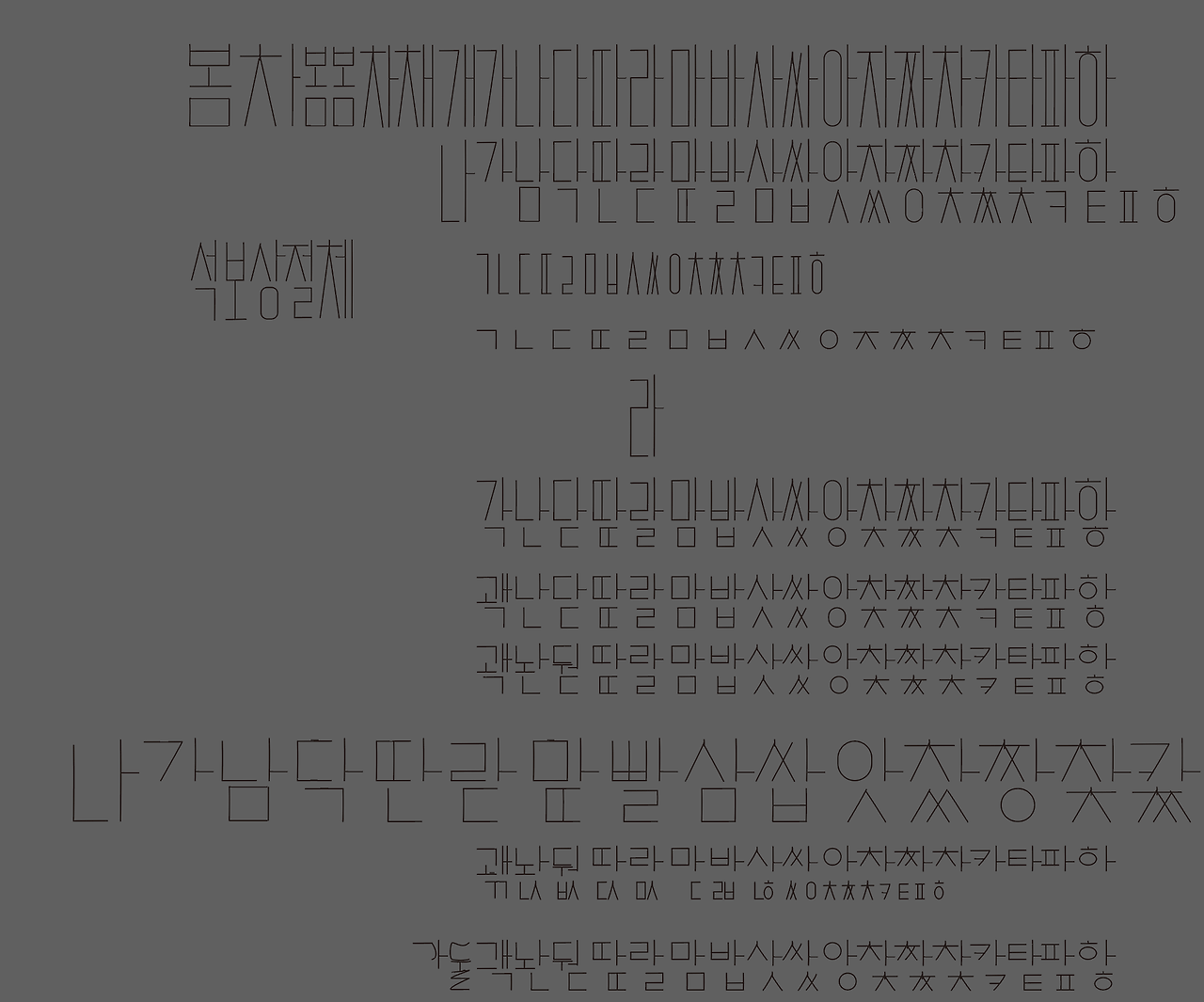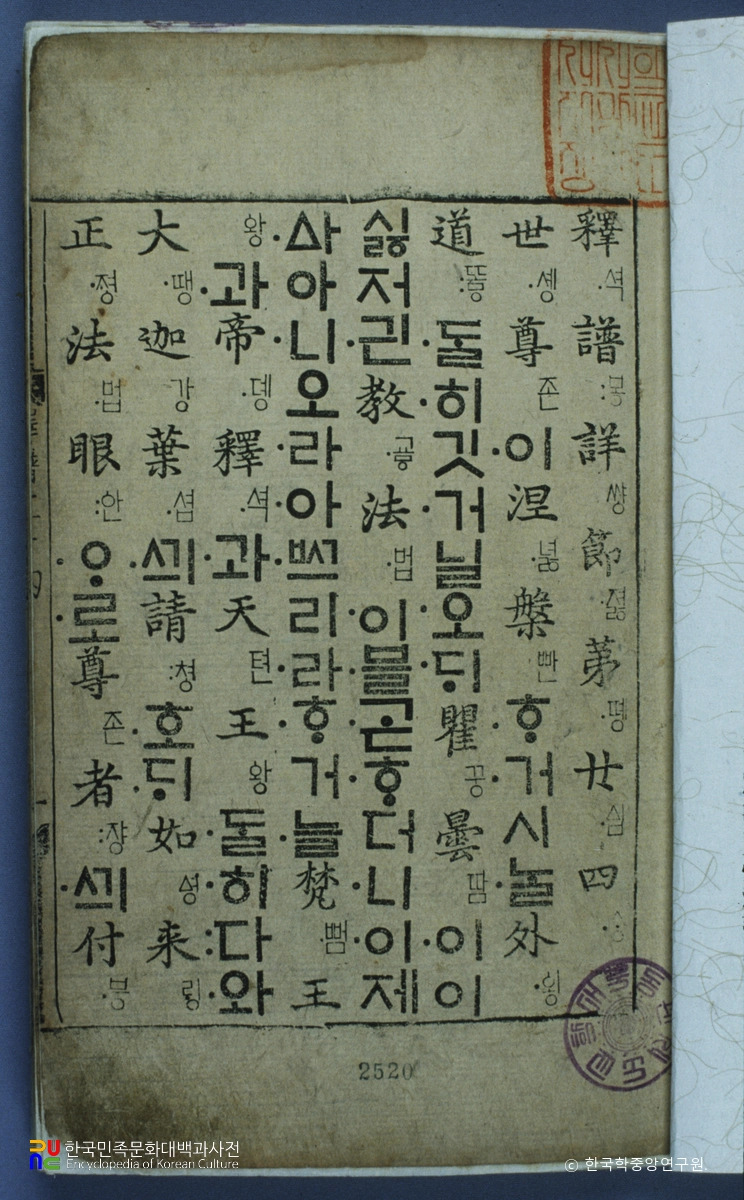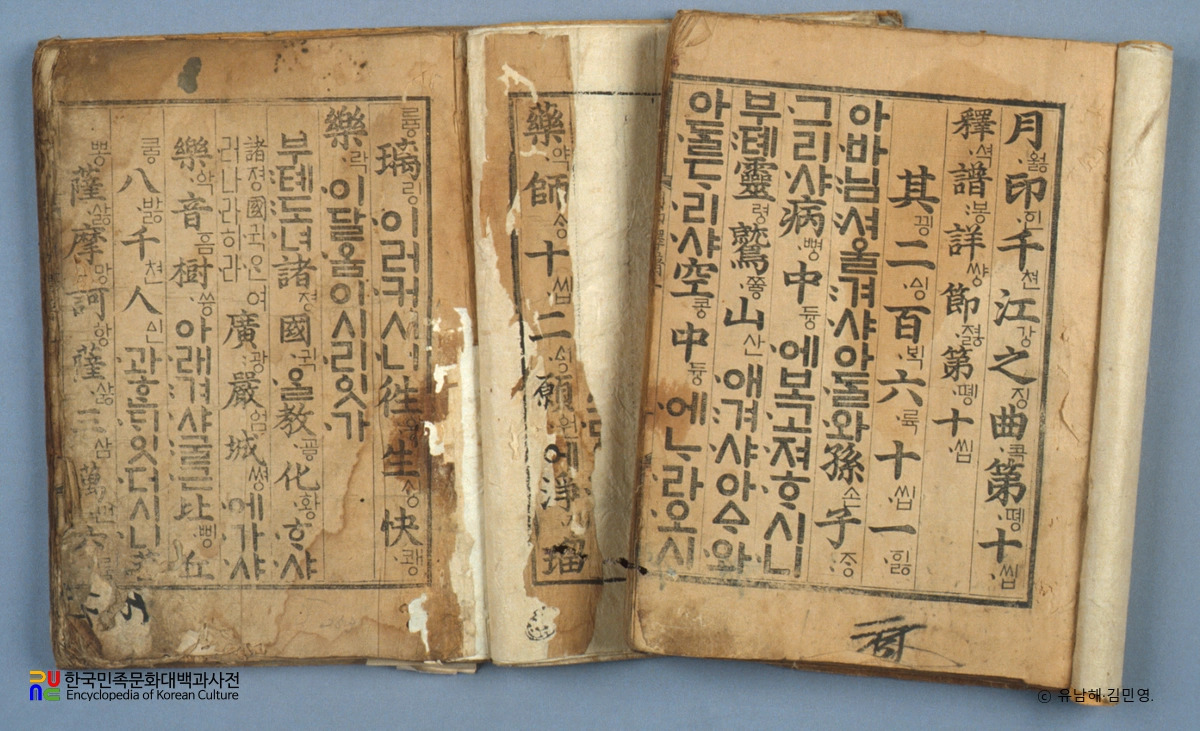
석보상절 폰트를 만들면서
수양대군이 간행한 석가모니의 일대기속 한글 폰트
석보상절은 조선 전기 1447년 수양대군이 간행한 석가모니의 가계와 그 일대기를 기록한 책. 7책. 보물 제523호. 조선 초기의 불교학 수준을 나타내고, 최초의 번역불경이라는 점에서 높이 평가된다. 동국대학교 중앙도서관 소장본 임
불교경전인데 한자에 한글을 음으로 차용하여 읽기 쉽게 구성한 것이 있는데 그 한글이 현대 한글 폰트와 유사해서 더 자세히 보게 된 계기가 되었다.
초기의 아학편의 금속활자와 다른 형태의 세로 비율길고 타자기 서체와 비슷한 느낌을 주며 현대의 고딕체와 유사하다. 그래서 다양한 자료를 모으고 석보상절의 자료를 한국민족문화대백과 사이트에서 다운받게 되었다. 추가적으로 월인석보의 글자도 자료로 검토중이며 기존에 제작된 폰트들에 대해서도 찾아보고 있다.
아직은 다른 형태이지만 곧 자료를 기반으로 한글벡터화 이후 라인드로잉을 작업할 계획으로 그동안 대충 만든게 너무 많아서 이번에는 공을 들여볼 생각이다.
비슷하면 다시 짜깁기해서 아주 빠른 시간에 재조합해 짜 맞출 수 있는 패스기반의 폰트 유형으로만 제작중